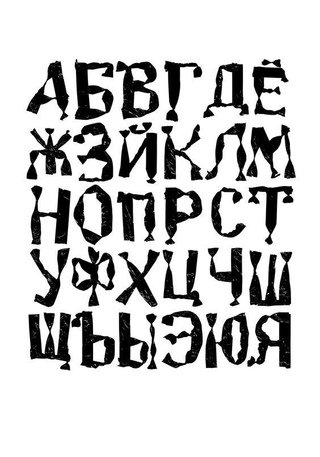
Серьезный шрифт: Русские шрифты | Шрифты онлайн
Типографика – знакомимся с популярными шрифтами
Одним из первых источников информации, который мы получаем с самого детства является текст. Он привычен для нас и понятен еще с небольших картонных книжек с веселыми картинками и крупными буквами. За восприятие текста человеком отвечает типографика. Типографикой называется процесс оформления текстовой части и графического дизайна сайта или другого проекта посредством применения разнообразных шрифтов и эффектов. Под ней также подразумевается графическое моделирование, которое выполняется при помощи встроенных средств конкретного языка, средств разметки (для веб-проектов) и возможностей графических редакторов, например, Photoshop.
Типографика и ее особенности
Типографика отвечает исключительно за текстовую часть страниц сайта, которая, как правило, в себе несет определенную информацию, касательно содержимого ресурса. Необходимость гармоничного оформления текста обусловлена степенью восприятия информации посетителями.
По самой простой классификации шрифты разделяются на…
антиква — имеет характерные засечки.
Итало-французская антиква в шрифте Adobe Garamond
гротеск — не имеет засечек, рубленный шрифт.
Пример шрифта гротеск – Helvetica
Различия между шрифтами антиква (с засечками) и гротеск (без засечек) хорошо иллюстрирует следующее изображение. Засечки выделены красным цветом.
Шрифты так же могут быть:
- Пропорциональными, где ширина букв у всех равна
- Моноширенными или непропорциональными, где буквы отличаются по ширине друг от друга;
- Символьными, состоящими из знаков, которые не относятся к буквам
- Акцидентными, сложные, художественные шрифты, предназначенные для офрмления малого количества текста, заголовков на плкатах, сайтах, афишах и так далее.
Пример акцидентного художественного шрифта.
Стоит так же упомянуть о следующих понятиях, которые нужно обязательно знать дизайнерам и тем, кто изучает типографику.
Кернинг – изменение интервала между буквами в зависимости от их формы:
Начертание шрифта – прямой, курсивный, жирный, полужирный и другие
Трекинг — расстояние между буквами вне зависимости от их формы.
Интерльяж — междустрочные интервалы. Если на первых порах вам сложно подбирать расстояние между строк, не расстраиваетесь, значение по умолчанию, будет смотреться гармонично.
Иерархия — это расположение текста, изменение его начертания, размера или шрифта таким образом, чтобы выделить наиболее важные части и показать откуда стоит начинать читать текст.
Некоторые базовые правила и советы
Грамотное оформление текста на сайте играет немаловажное значение при его прочтении.
Именно поэтому каждому верстальщику рекомендуется хорошо поработать над этим навыком, чтобы представлять свою работу в более привлекательном и приятном свете. Если дизайн сайта – это обертка, то типографика – это начальный аромат блюда, представленная же с помощью этих инструментов информация отражает вкусовые ощущения. Чтобы научиться правильно выбирать размер шрифта для заголовка, всего содержимого, его стиль или прочую атрибутику, необходимо четко знать базовые правила в этом искусстве:
1. Крайне не рекомендуется применять для оформления делового текста причудливый (акцидентный) шрифт. Он будет смотреться броско и не к месту. Как правило, подбирают шрифты для сайта исходя из его тематики. Если в контексте содержится юмор, то в таком случае можно пренебречь правилом.
2. Многие считают шрифты семейства Trajan старинным и даже причудливым, но это неверное суждение, потому что он отлично вписывается в различные исторические сайты.
Необходимо научиться им правильно пользоваться. К тому же он есть на Google Fonts.
3. Не стоит использовать в оформлении типографики сайтов Comic Sans. Изначально данный шрифт создавался для имитации написанных от руки букв комиксов и не предназначен для оформления серьезных тем. Большинство пользователей считают его нечитабельным для большого объема информации. И чаще всего используется в играх, афишах, небольших заголовков.
4. Не стоит отвергать бесплатные шрифты, предлагаемые редакторами по умолчанию, например, Times (New) Roman. Это красивый, пусть и надоевший всем вид оформления текста. Он используется из давних времен, поэтому кому-то может и приелся. Лучше не отказываться от него, а научиться правильно использоваться, выбирая размер и прочие атрибуты. Даже при оформлении с его помощью заголовка будет смотреться стильно и по-деловому. На самом деле он является уникальным и многофункциональным.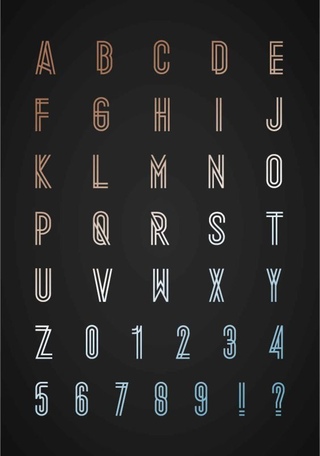
5. Очень выгодно в оформлении сайтов и мобильных приложений смотрится шрифт Sans Serif. Он выглядит по-деловому.
6. Одно из главных правил типографики — ЧЕМ ПРОЩЕ, ТЕМ ЛУЧШЕ! Ограничьтесь одним, двумя шрифтами, а если хотите больше разнообразия — изменяйте начертание или размер шрифта.
Классические и трендовые шрифты
Правильно подобранный тип шрифта только положительно сказывается на восприятии информации, представленной на сайте. Поэтому, если не знаете, какой все-таки применить, лучше использовать классический тип.
Serious3b, Обычный
Шрифт Serious3b является одним из вариантов шрифта Serious, который имеет стиль Regular. Этот шрифт имеет формат ttf и поддерживает 127 глифов. Исходя из метрики шрифта, Serious3b Regular имеет вес 400, ширину 5 и угол курсива 0. Этот шрифт обозначен как.
Серьезный4, Обычный